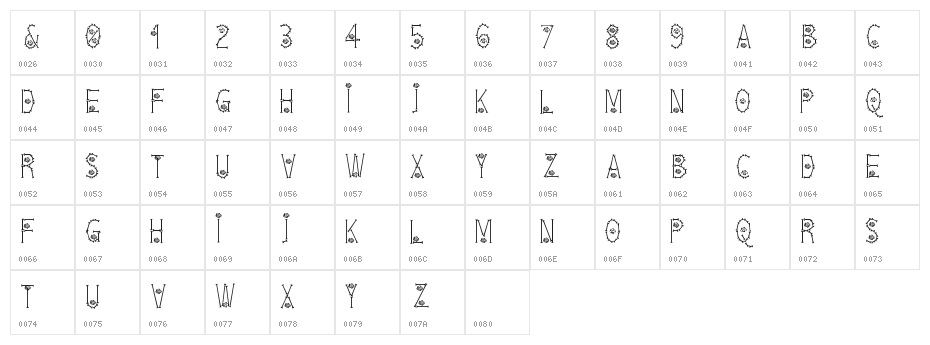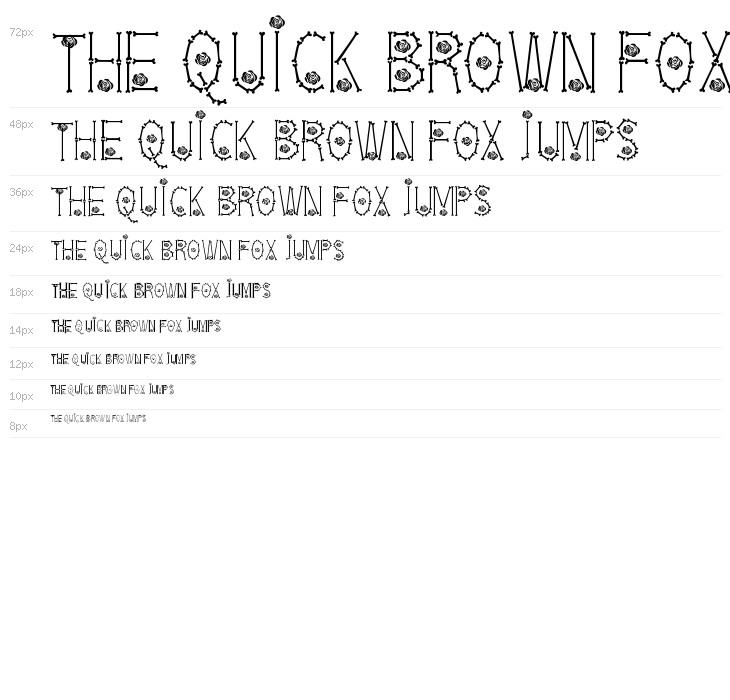
Bones Roses Thin Font
| Stile generale | Gothic, Decorative |
| Caso d'uso | Logos, Posters, Artistic Titles |
| Progetti proposti | Ideal for Halloween-themed designs, gothic art projects, album covers, or any creative work requiring a dramatic and artistic touch. |